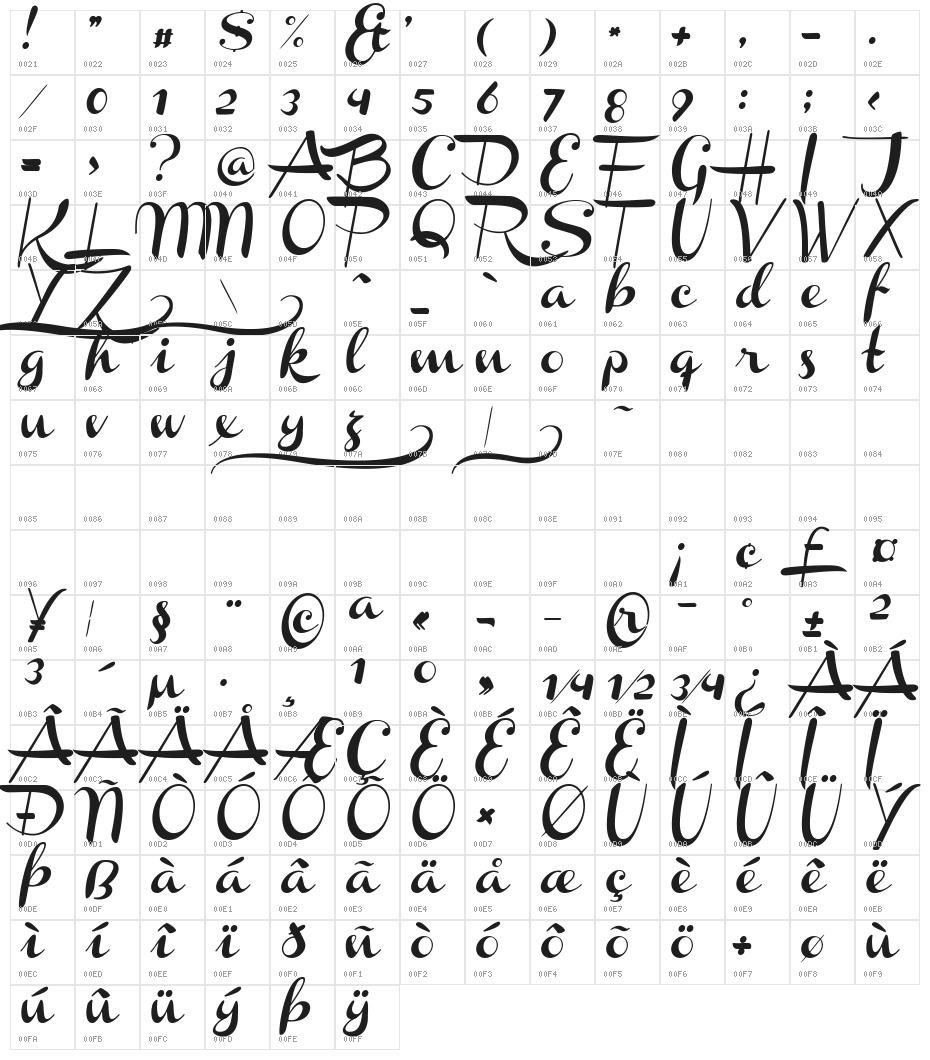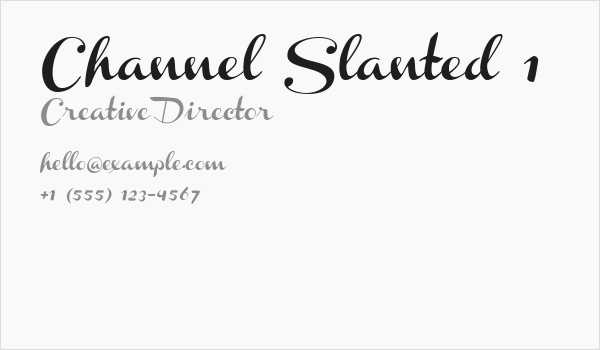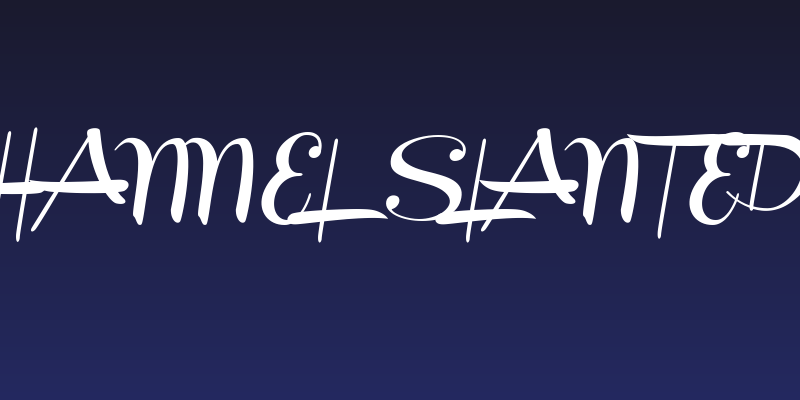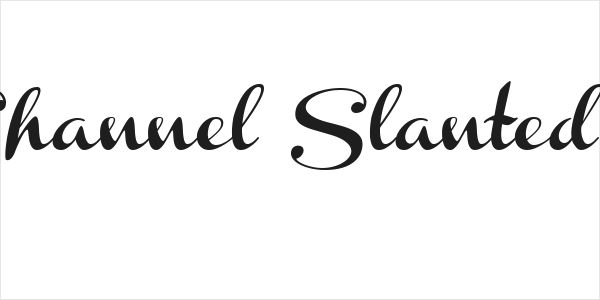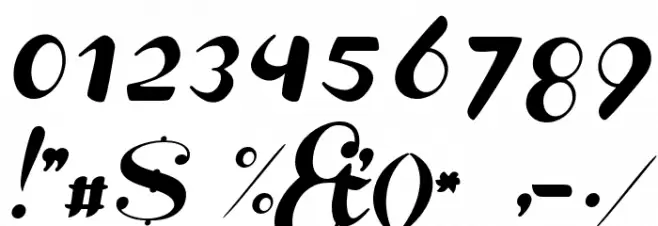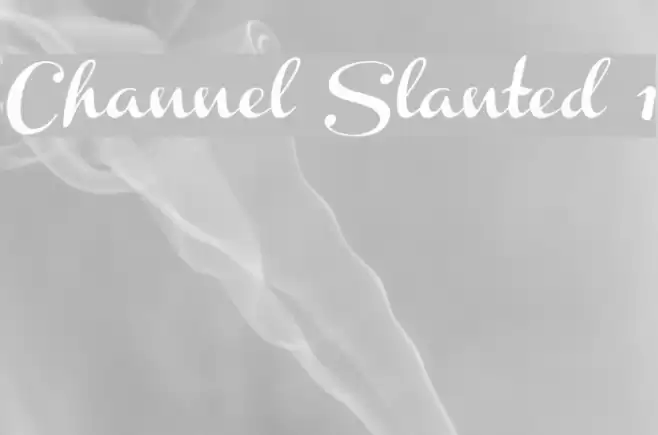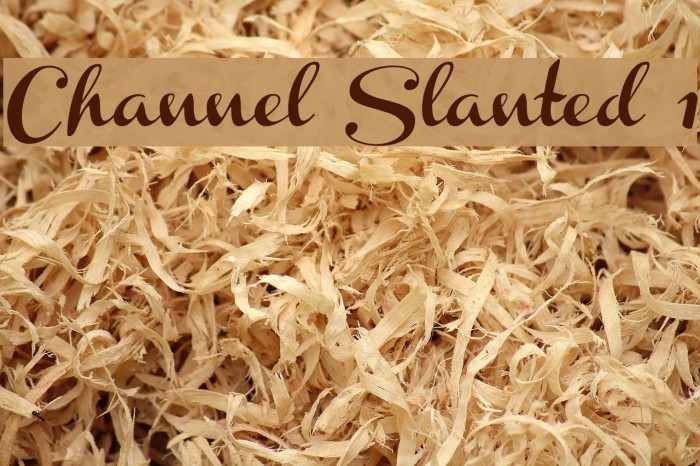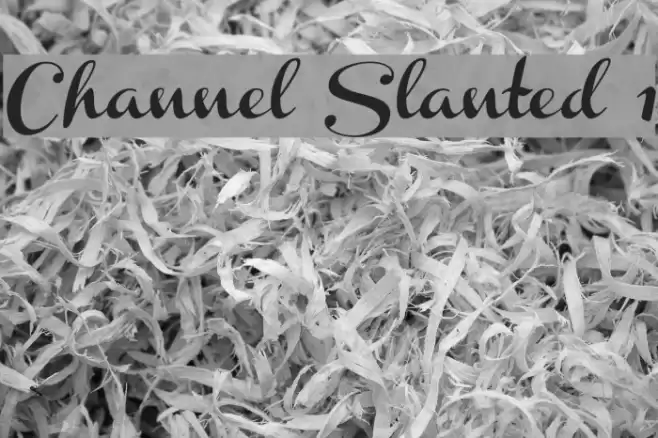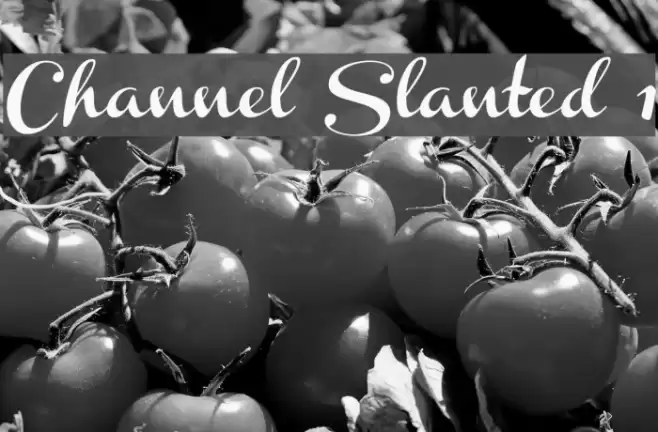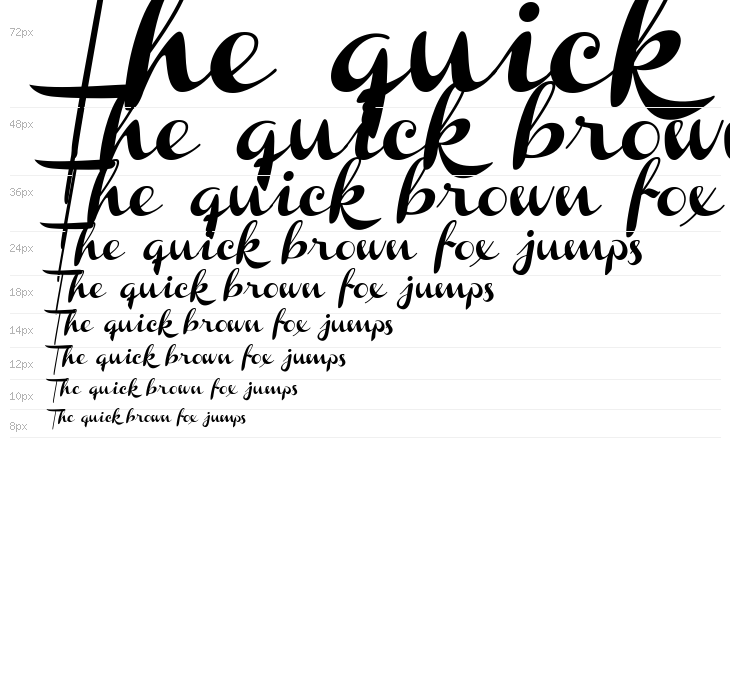
Channel Slanted 1 Font
| おすすめプロジェクト | Ideal for creative projects such as branding, invitations, posters, and artistic designs where a touch of elegance and movement is desired. |